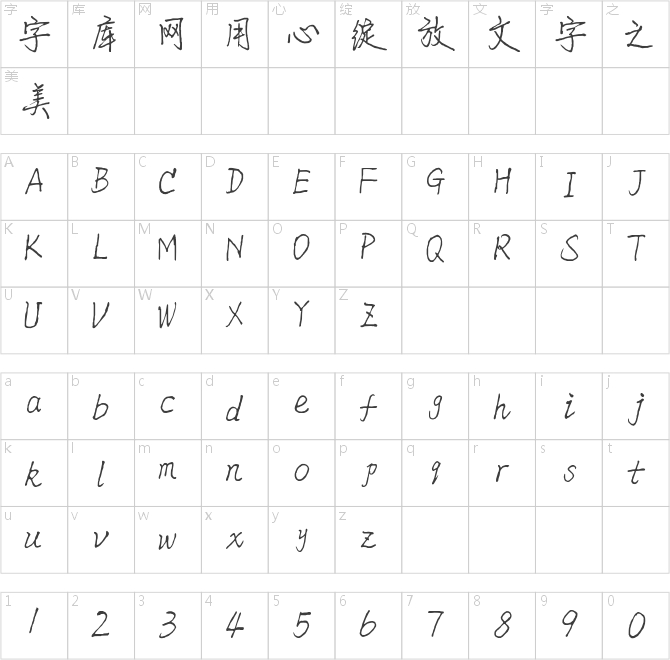
字體名稱: 少年體
作者版權(quán): 方正手跡
少年體
少年體介紹
少年體是一款優(yōu)秀的硬筆書寫字體。字體筆畫硬朗瘦勁,起筆轉(zhuǎn)折多用方筆,字形灑脫俊逸,筆意連貫,節(jié)奏感十足。亦如少年兒郎,英姿勃發(fā),意氣十足。適用于文藝類的書刊、品牌廣告和產(chǎn)品包裝設(shè)計,現(xiàn)代詩歌、短文排版,綜藝影視字幕用字,以及社交網(wǎng)絡(luò)的個性化用字。